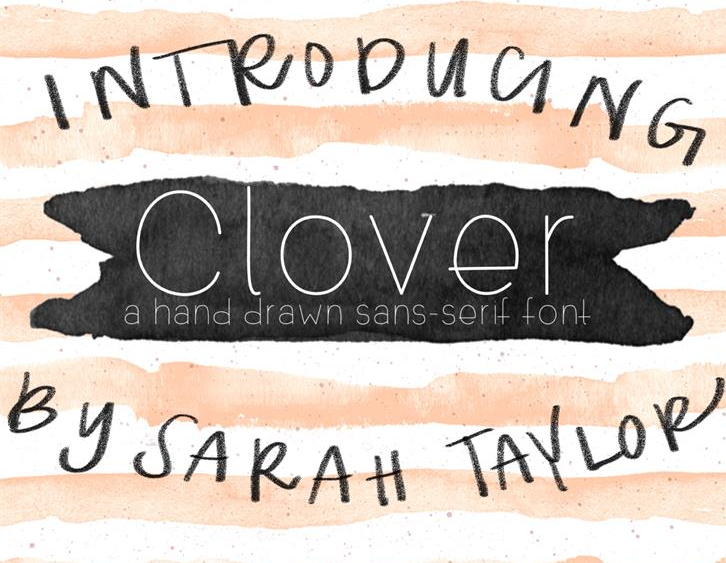
Clover Font – Fonte Grátis
Clover Font
A fonte Clover é uma evolução moderna de um tipo de sans-serif simples. SarahTaylorDesigns apresenta essa tipografia como um ótimo complemento para qualquer projeto, especialmente quando se trata de destacar títulos e incorporar textos em corpo. Suas linhas limpas e design minimalista tornam-a perfeita tanto para aplicações no topo da página quanto para o texto central. Clover atende às necessidades modernas do mundo digital, oferecendo uma escolha atraente entre os muitos tipos de fontes disponíveis atualmente. Seja você um designer gráfico ou um criador de conteúdo online, Clover pode ser a adição perfeita ao seu arsenal de recursos visuais.
Designer: SarahTaylorDesigns